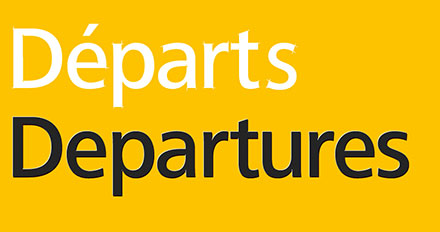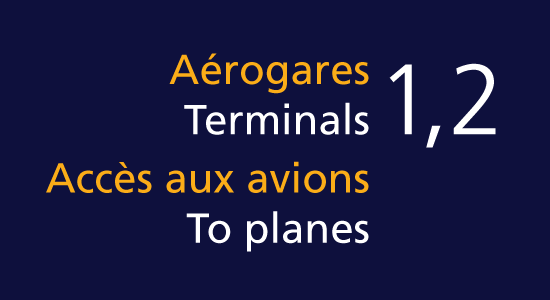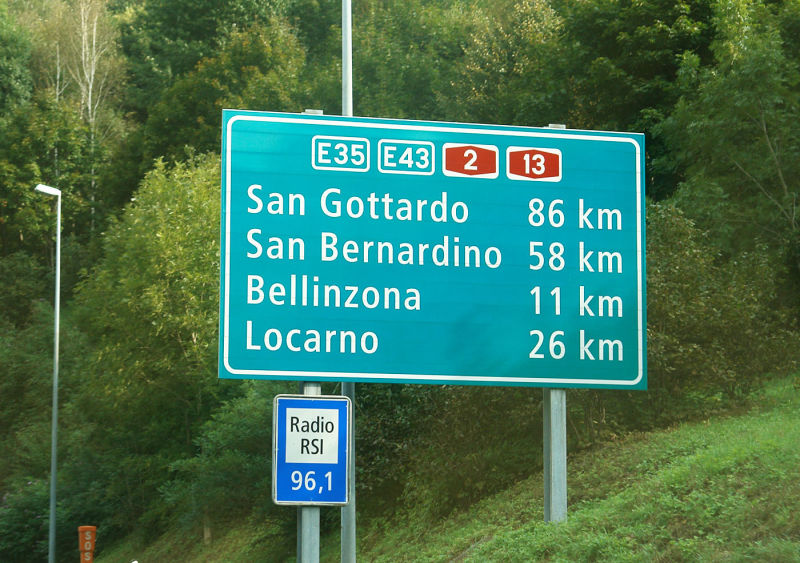
Tutti l’abbiamo visto senz’altro da qualche parte: stiamo parlando del font Frutiger, carattere senza grazie creato dal designer svizzero Adrian Frutiger, morto a 87 anni e creatore di questo e altri apprezzati caratteri tipografici. Il tipografo svizzero era nato nel 1928, aveva cominciato a lavorare occupandosi di composizione tipografica cimentandosi allo stesso tempo con la calligrafia, disegnando caratteri nel tempo libero. A un certo punto Frutiger andò a lavorare alla fonderia parigina Deberny Et Peignot, all’epoca in cui erano di moda l’Helvetica e il Futura, caratteri che stimolarono (quando aveva solo venti anni) la creazione di un nuovo carattere senza grazie, l’Univers. Questo piccolo e comodo font fu sfruttato su iconici segnali stradali britannici, dal Bay Area Rapid Transit (BART) District della San Francisco Bay, ma anche da molti brand noti, inclusa Apple che usò il carattere in questione sulle tastiere prima di passare al “VAG“.
Il Frutiger fu commissionato nel 1968 per l’aeroporto Internazionale Charles De Gaulle di Roissy (Parigi), all’epoca in costruzione, che aveva bisogno di un nuovo sistema direzionale di insegne. Invece di usare uno dei suoi font, come il già noto Univers, Frutiger preferì crearne uno nuovo. Il nuovo carattere, inizialmente chiamato Roissy, fu disponibile nel 1975 e usato nell’aeroporto lo stesso anno. Tra le peculiarità di questo font, l’aspetto moderno, la razionalità, la pulizia, la particolare leggibilità, caratteristiche che erano state espressamente richieste dai dirigenti del Charles De Gaulle (il carattere doveva apparire chiaro e coinciso sui tabelloni luminosi e sui cartelli e si dice che Frutiger partì dalle scritte “Dèparts” e “Departures”).
Il font è ora usato in tantissimi altri contesti (anche dalla rete di trasporto pubblica di Oslo, in Norvegia) e pare sia il carattere di maggior successo della Linotype. Tra le sue tante imitazioni, il Myriad di Adobe e il Segoe UI di Microsoft. Al pari di altri caratteri sono nate varianti corsive e inclinate; l’ultima è stata denominata Frutiger Next. La prossima volta che vi recate in aeroporto, pensate un po’ anche a questo signore… se riuscite immediatamente a individuare l’area per recuperare i bagagli è anche merito suo.